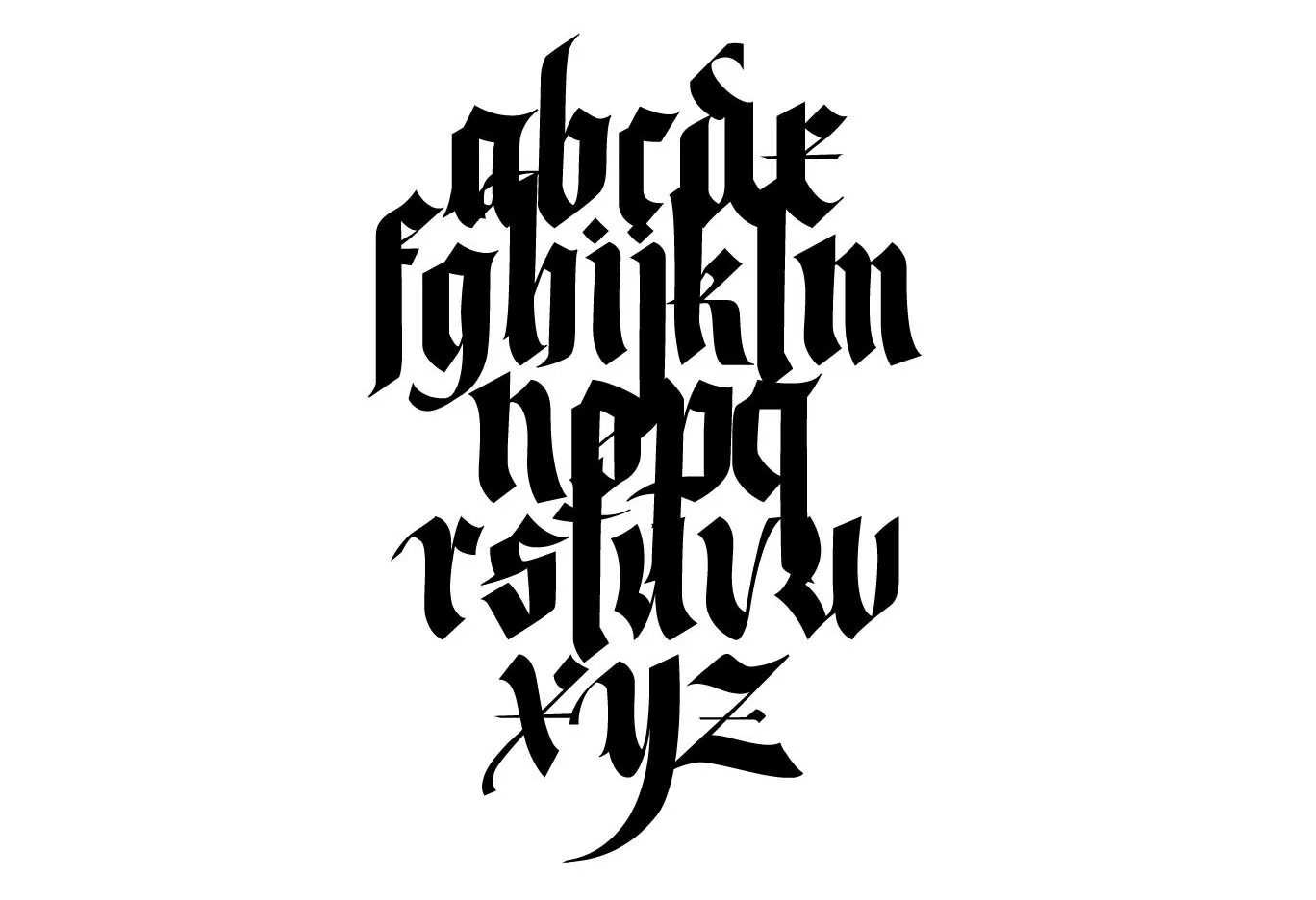
A Abuso é uma fonte inspirada na cultura do calligrafie, que é uma arte que mescla a tipografia, a escrita e a grafite. Esta fonte se enquadra tanto no estilo de expressão abstrata quanto na vandalismo abstrato. A Abuso font é perfeitamente adequada para gráficos com conteúdo agressivo e comunicações impactantes. Se você está em busca de uma fonte que dê vida à sua próxima campanha publicitária, essa pode ser a opção certa. Seu design único permitirá que você destaque seus esforços no meio de uma multidão, oferecendo um toque de criatividade e originalidade. Não importa o tipo de conteúdo que você está trabalhando em, a Abuso font tem sua atenção.